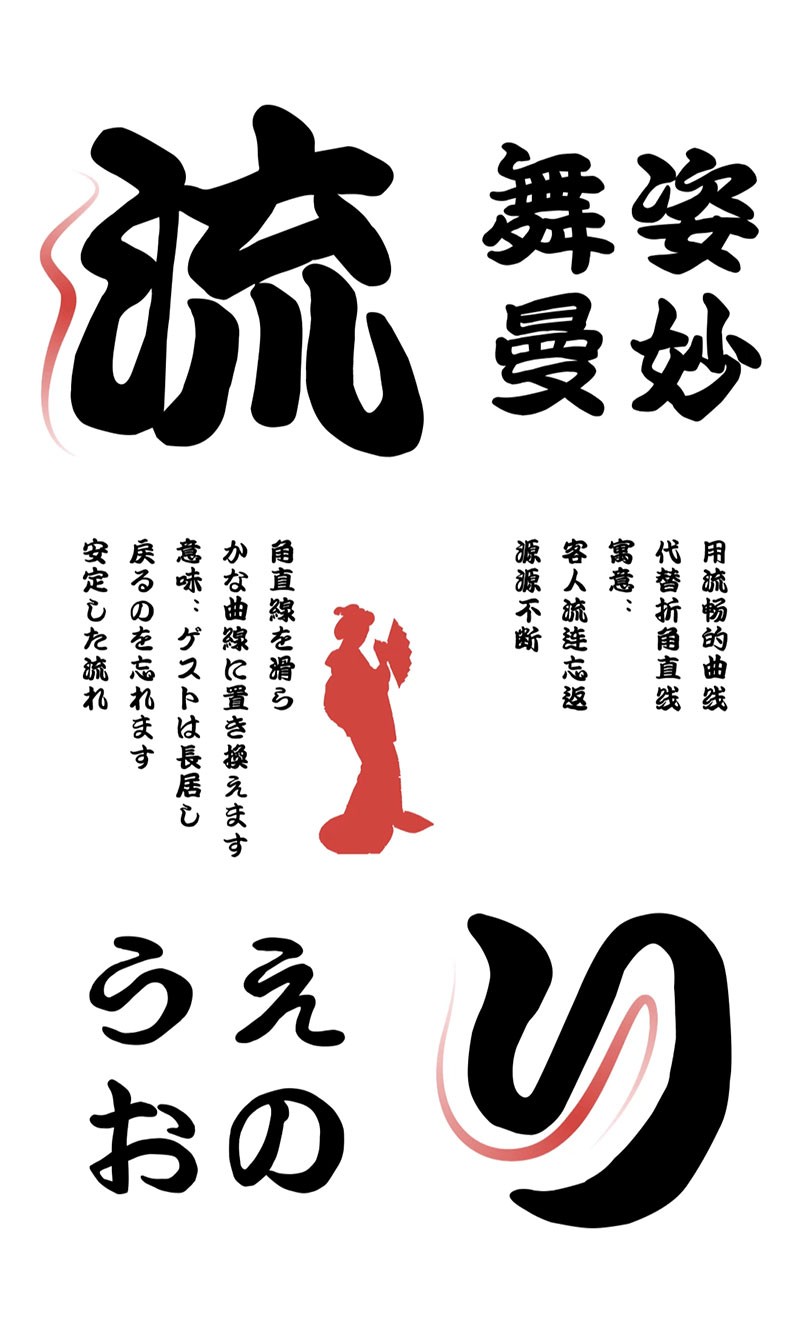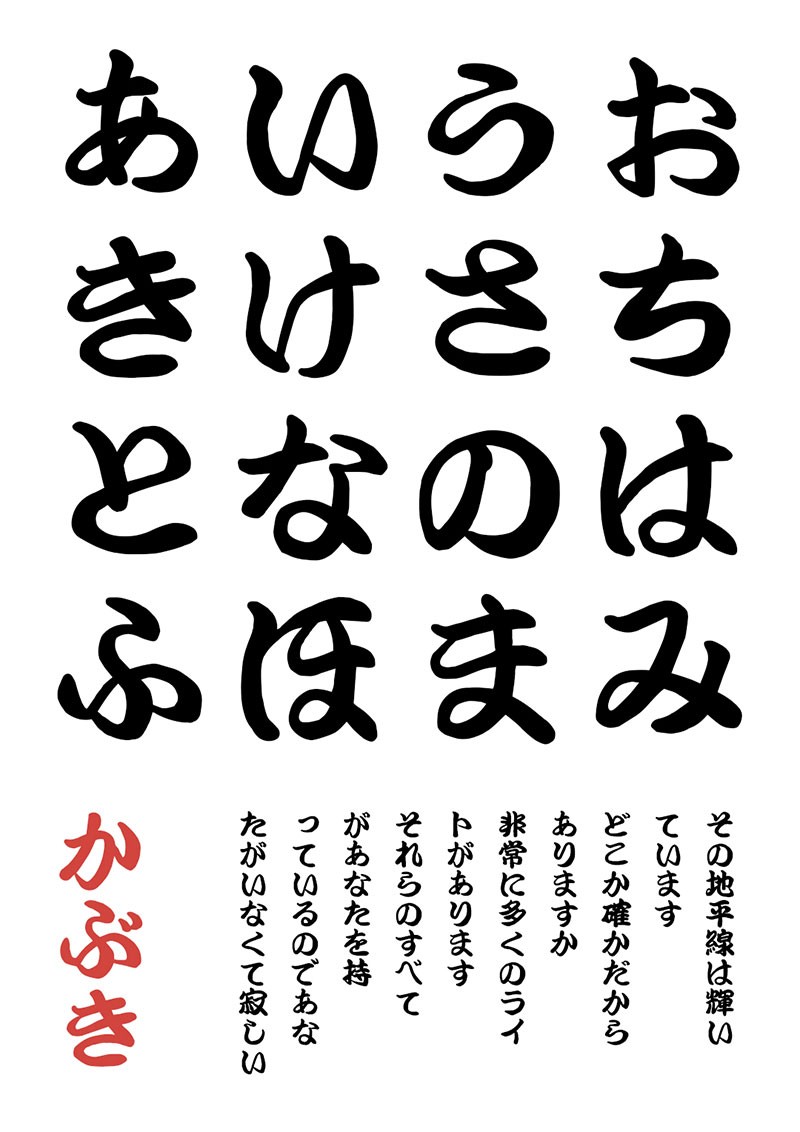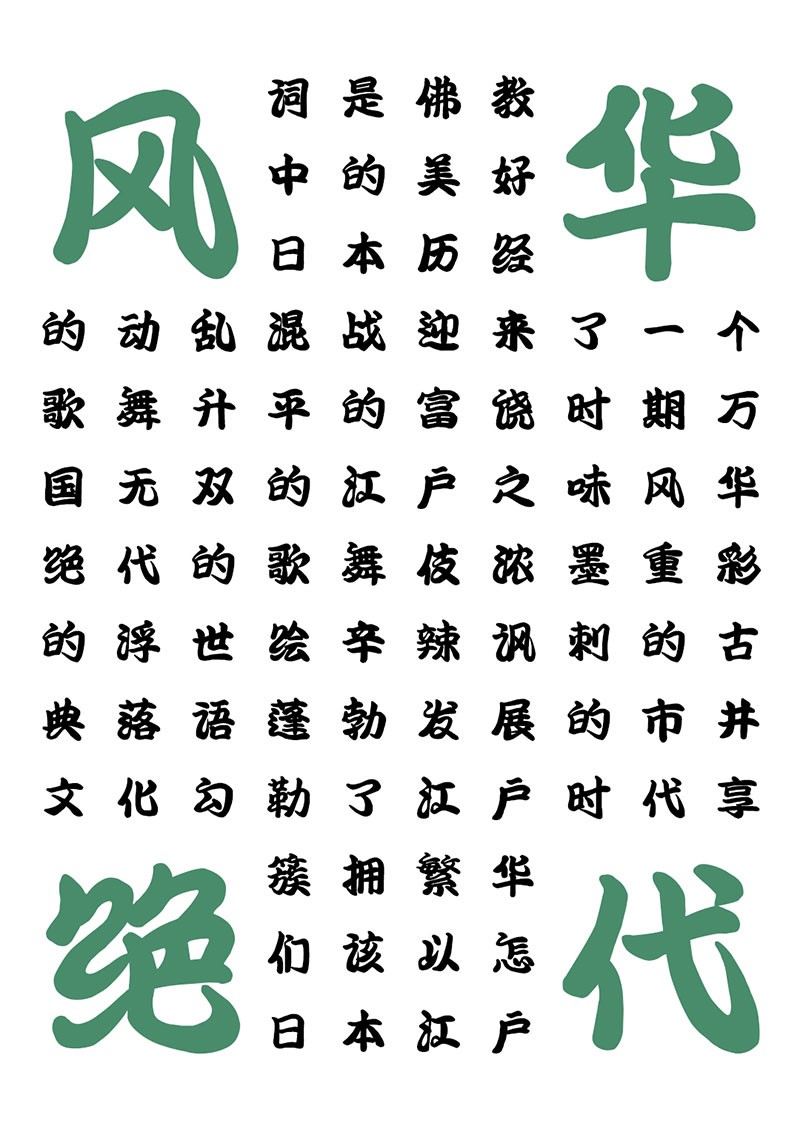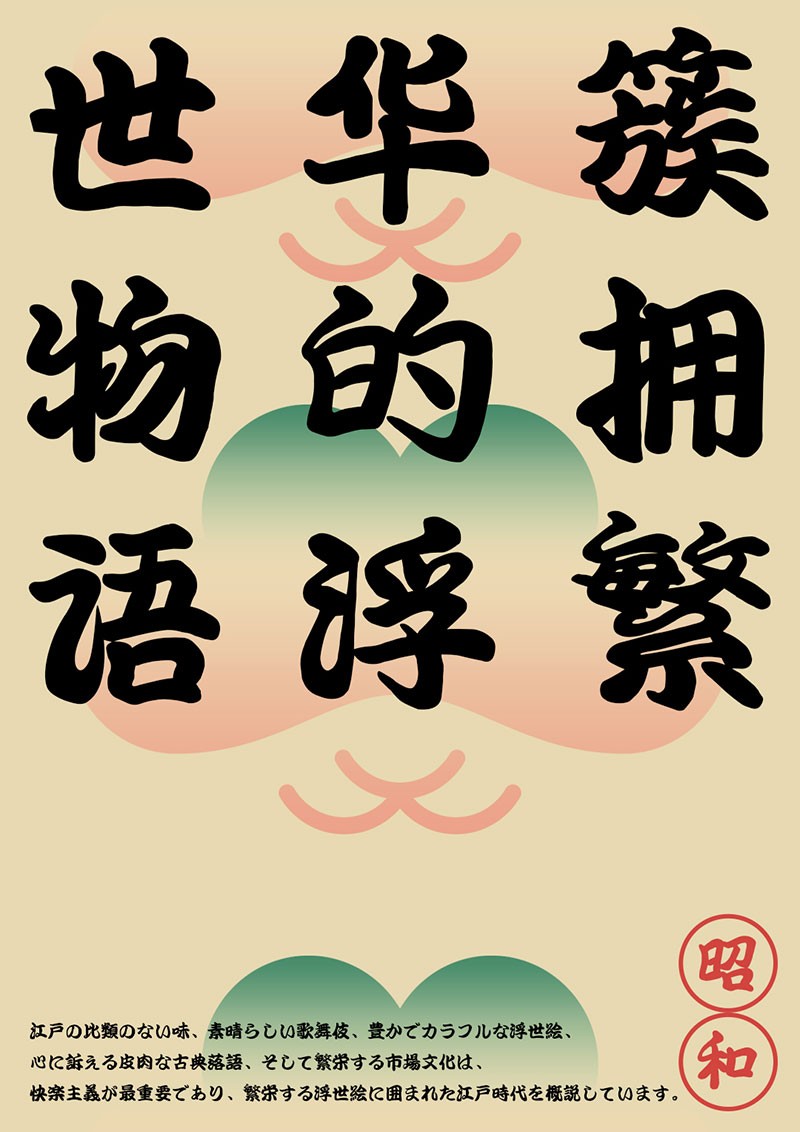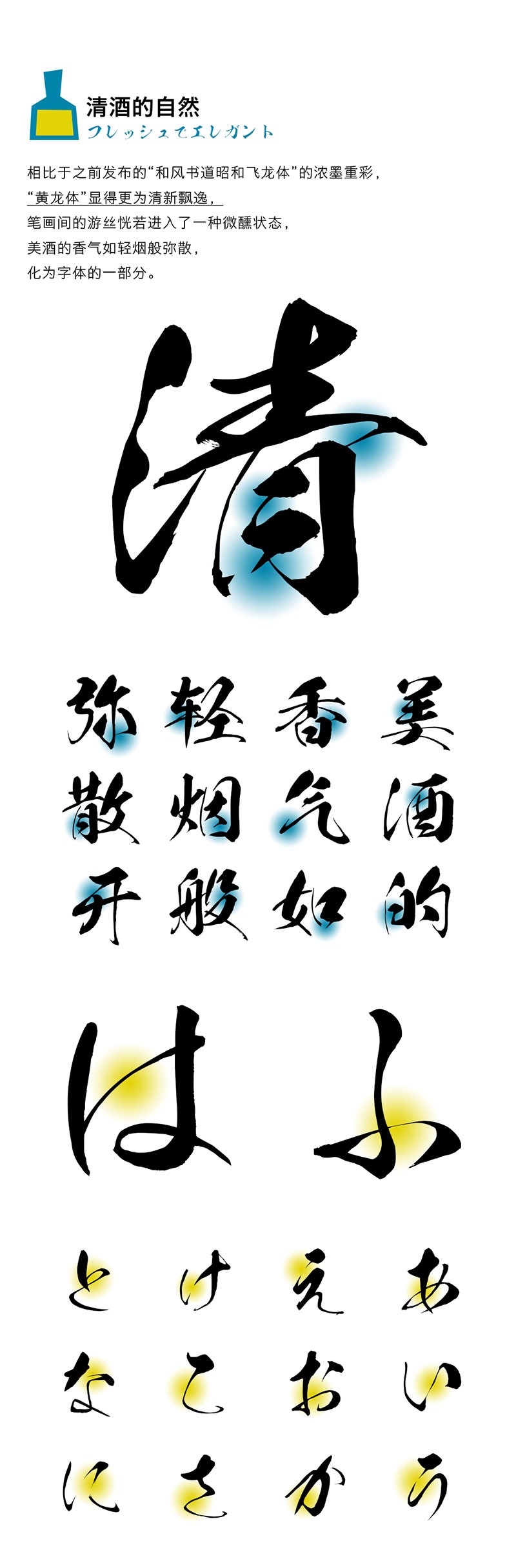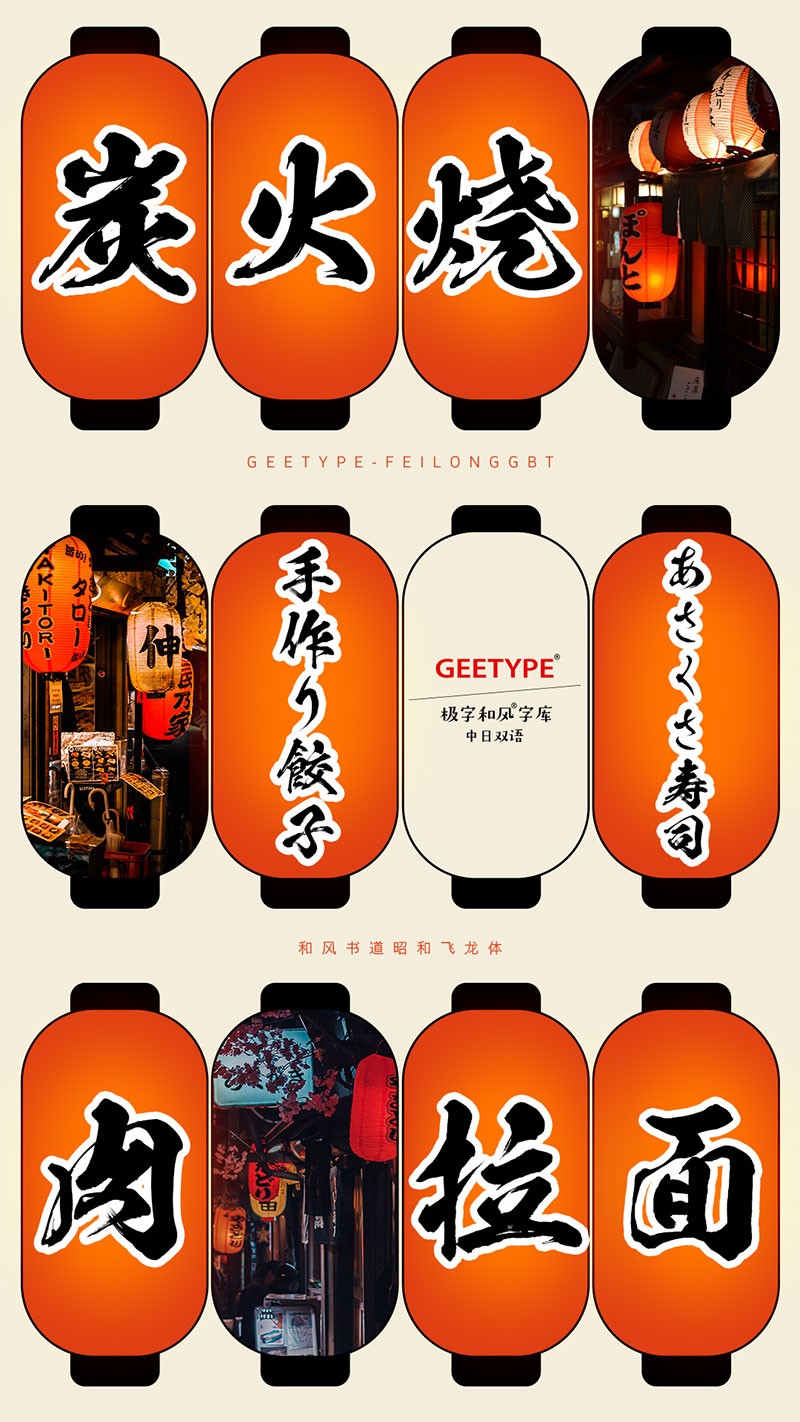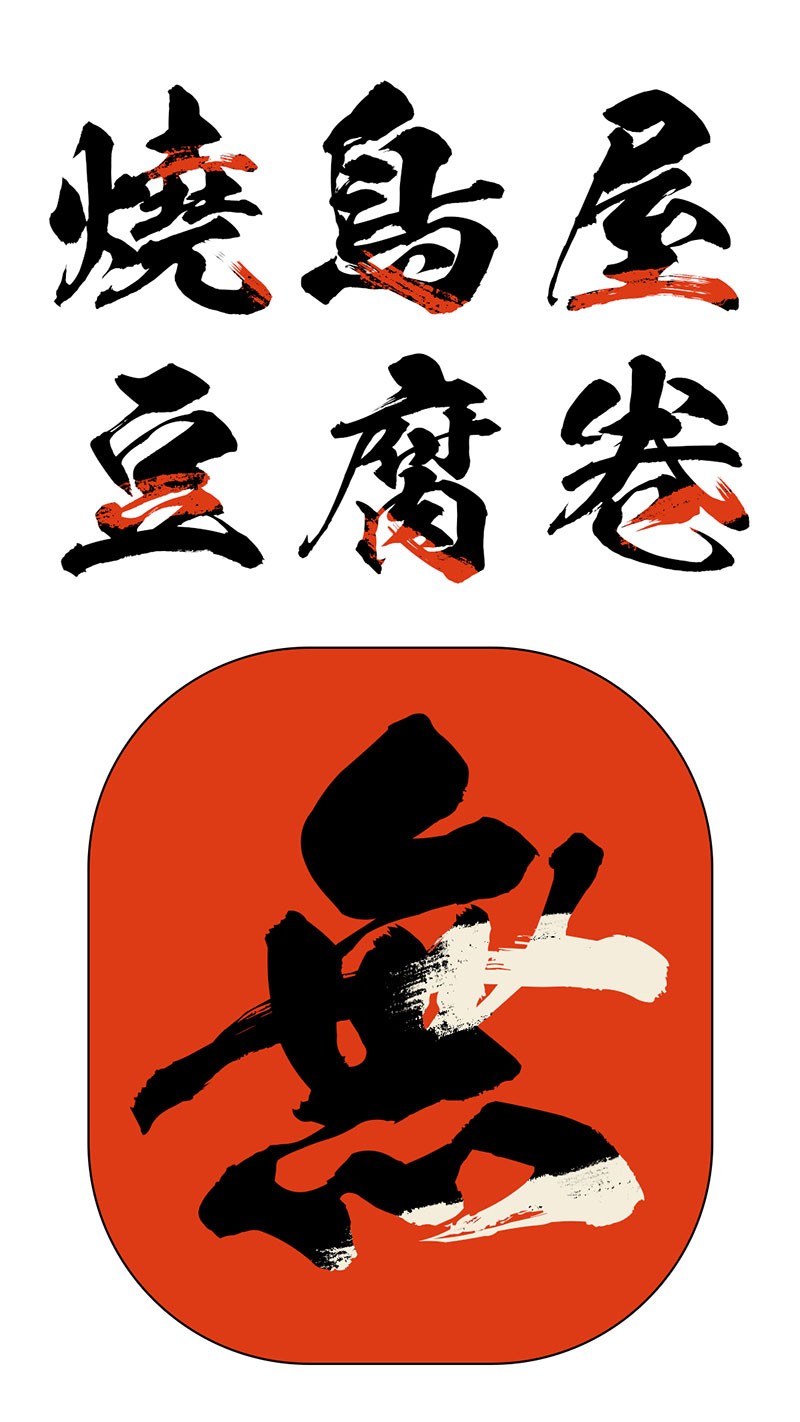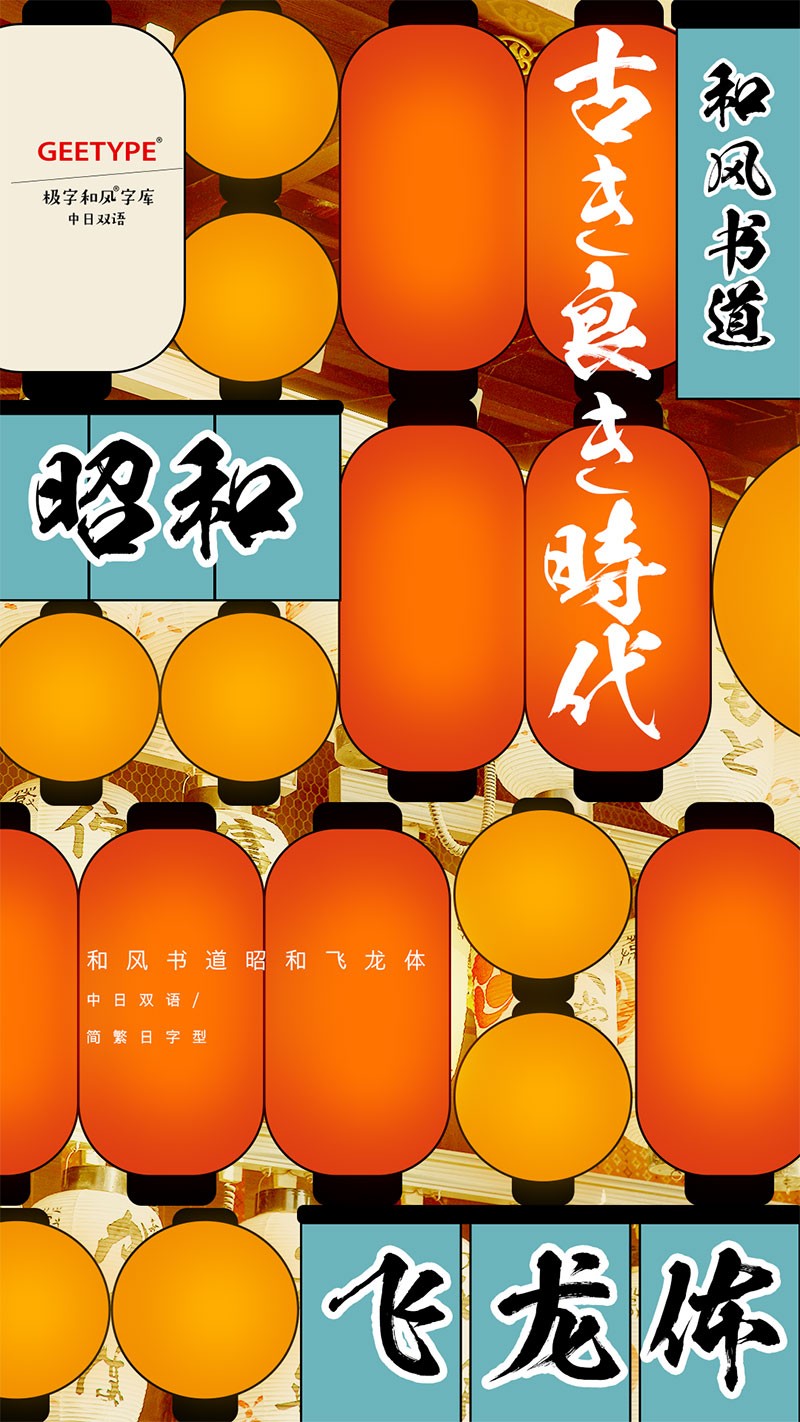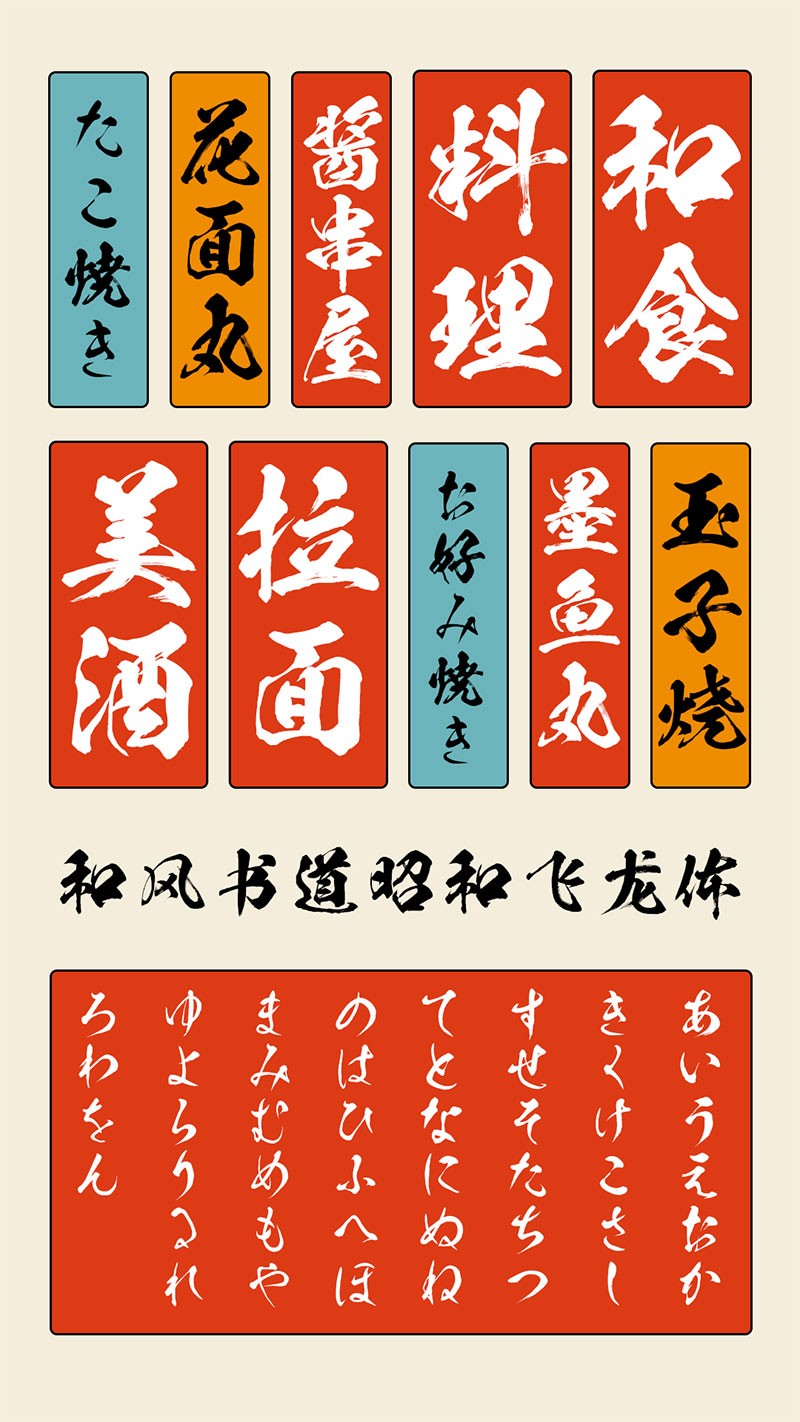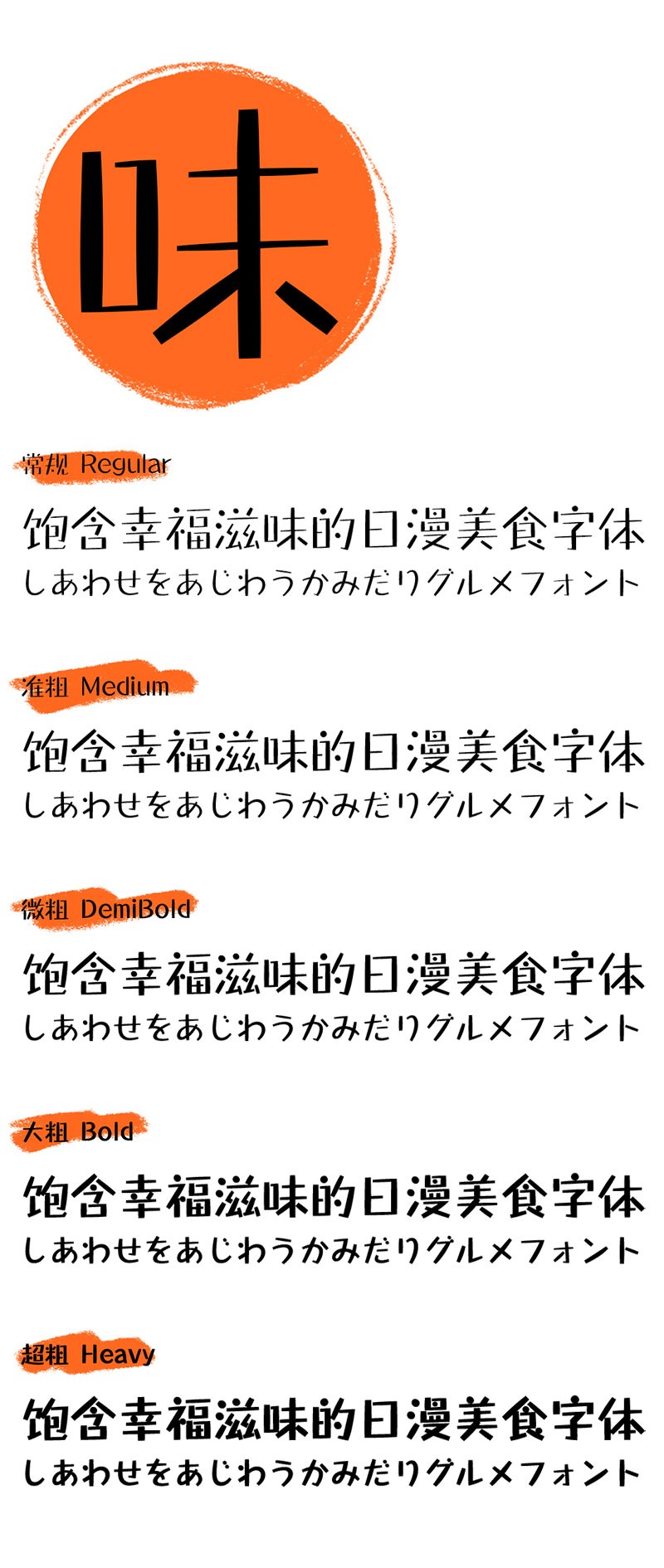
6款日系风格的海报字体
GEETYPE极字和风字库,为您带来了6款日系风格的创意字体。这些字体不仅支持中文和日文,还融入了浓郁的日本风情,展现出独特的艺术美感和创意性。不论您是设计作品、插画、海报还是手册,这些字体都能为您的作品注入独特的视觉魅力。
和风书道昭和勘亭流
和风书道昭和勘亭流体,提供简繁字形,中日双语,根据不同的设计风格进行语言字形选择,丰富应用场景。华丽饱满独具特色的书法字体,适合海报大字、封面屏幕,可以广泛应用于电影海报、美食、动漫、艺术展、短视频等多元领域。
和风书道昭和黄龙体
和风书道昭和黄龙体,提供简繁字形,中日双语,根据不同的设计风格进行语言字形选择,提升设计效率。兼具力量与灵气的书法字体,适合标题大字,可以广泛应用于酒类产品、电影海报、美食、动漫等领域。
和风书道昭和飞龙体
和风书道昭和飞龙体,提供中日双语版本。假名部分同样笔墨横姿,铁画银钩,蕴含着一种精神气格与韵律气象。带有浓郁昭和风味的「和风书道昭和飞龙体」,还可以应用于传单、海报、产品包装、动漫、广告、游戏等领域。
GEETYPE颜漫体
一款以手写感为设计基础的直线字体,弧度饱满的笔画,柔和简约的直线字形,轻盈卡通的手写感,仿佛置身舒缓治愈的漫画中。提供中日双语简繁日字形,可体验多元的应用。设置了常规、准粗、微粗、大粗、超粗5款字重,且支持可变字体,可随心调节字体粗细,匹配设计应用的不同排版需求。
GEETYPE晴空丸体/泡泡体
两款可爱而温馨的中日双语字体,笔画圆润,活泼俏皮,同时拥有轻松温暖的美感,给人感觉更加亲近,排列起来错落有致,生趣盎然。